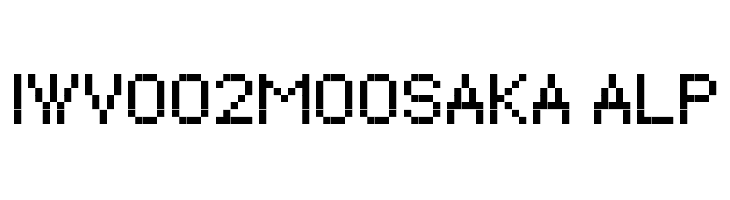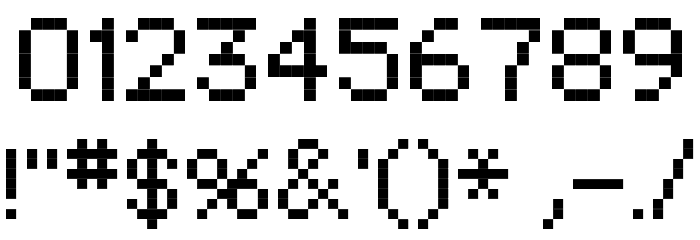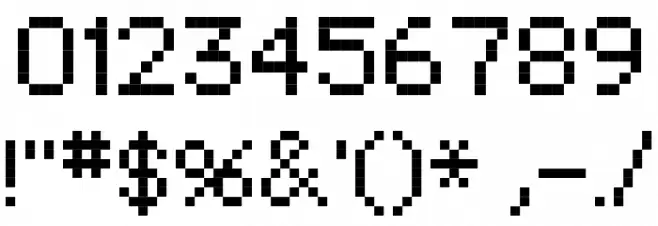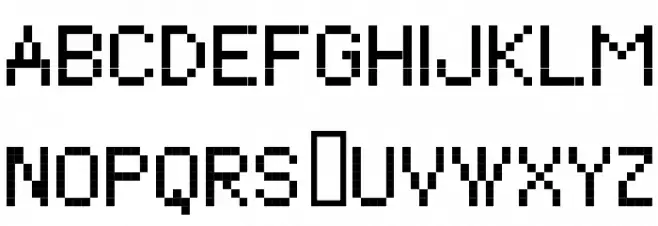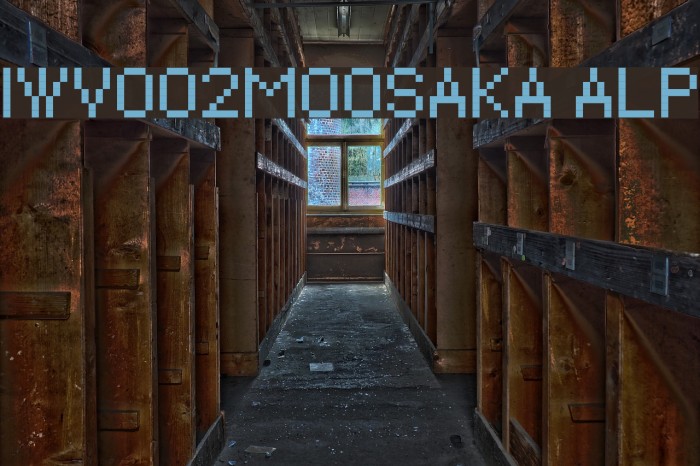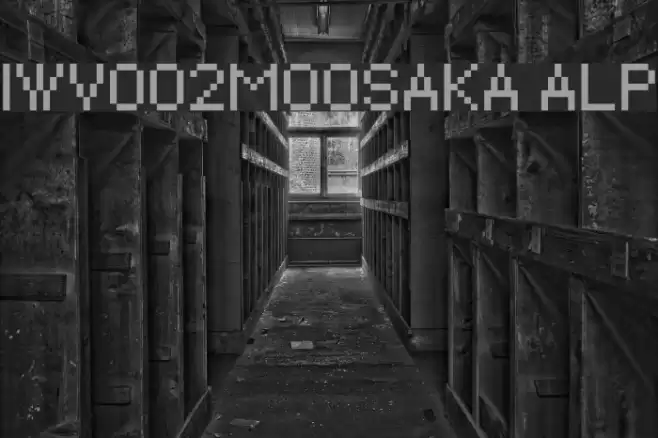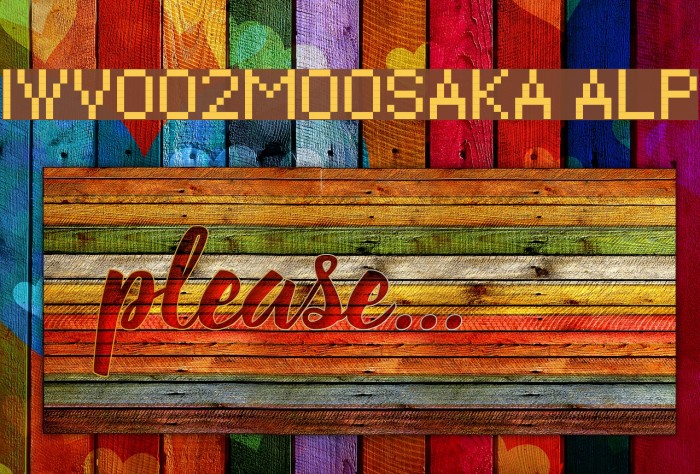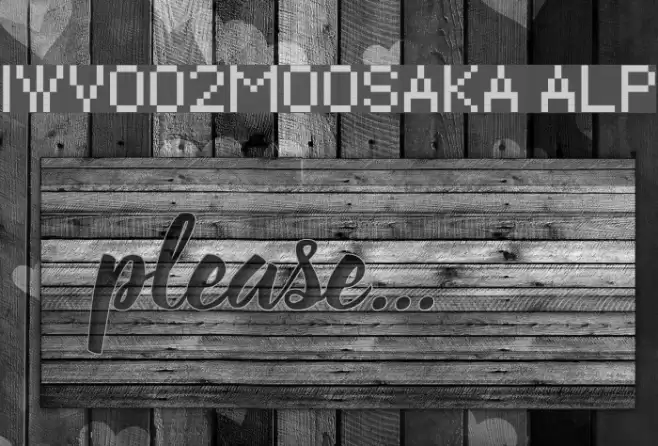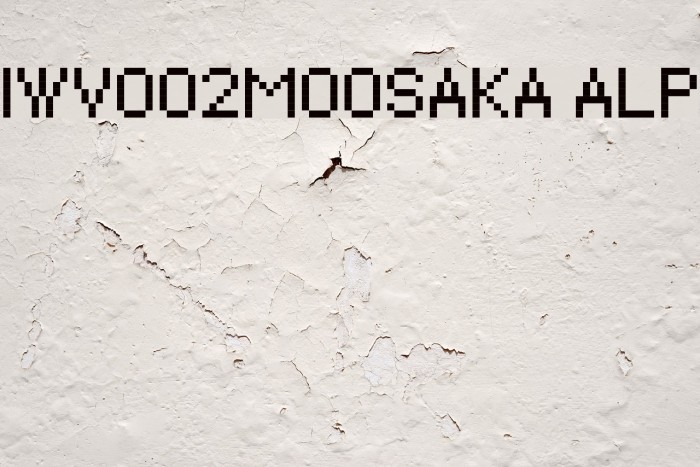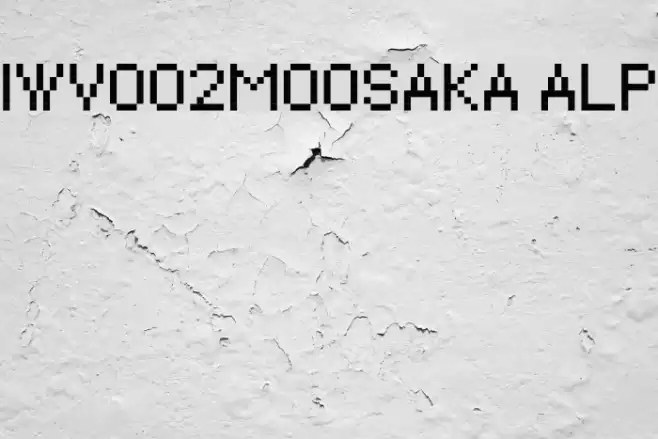
IWV002MOOSAKA ALP Font
| Kategorien | Pixel |
| Gesamtstil | Retro, Digital |
| Anwendungsfall | Headlines, Logos, Digital displays |
| Vorgeschlagene Projekte | Ideal for video game design, retro-themed posters, digital art projects, and tech-related branding. |